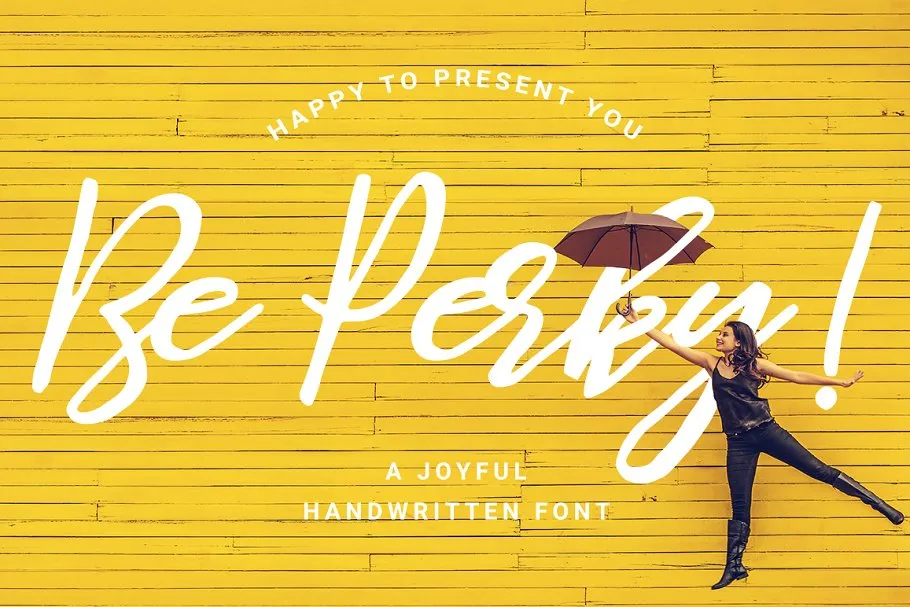
Be Perky! Handwritten Font – Download Grátis
A fonte ‘Be Perky! Handwritten Font’ é uma seleção perfeita para criar designs autênticos e elegantes. Esta é uma tipografia escrita à mão moderna, com um estilo suave e nuances sofisticadas. É o tipo certo para adicionar um toque de autenticidade ao seu logotipo, rótulos ou cartões-postais personalizados, citações escritas a mão em sua propaganda, coberturas de livros ou capas de álbuns, revistas, campanhas fashion e até mesmo em seus materiais de newsletter. Suave e natural, esta fonte é perfeita para quem busca um ar genuíno que se assemelha à escrita a mão por um charme autêntico. Seja na sua marca digital ou em seu próximo projeto gráfico, Be Perky! Handwritten Font oferece uma opção perfeita para manter o estilo de suas ideias de maneira única e envolvente.